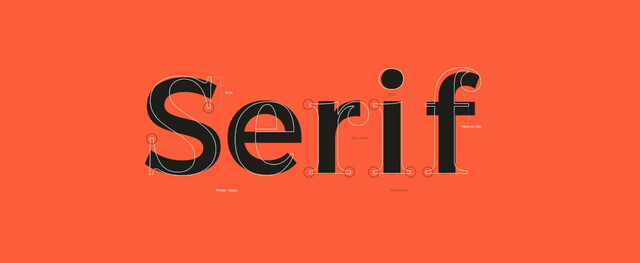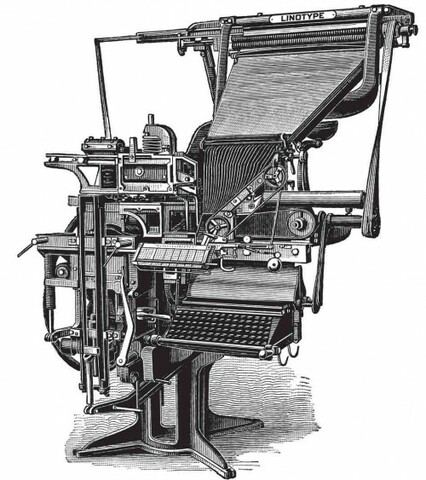
Alrededor de 1440, Johannes Gutenberg desarrolló en Alemania una técnica para elaborar moldes de tipo (ya conocida en China siglos atrás) que se utilizarían para la impresión de letras individuales, escogiendo el tipo textura como modelo, un tipo similar al trabajo de los escribas de la época. Fue con esta técnica que imprimió la Biblia de 42 líneas, la cual estuvo vigente por 500 años.
En 1486, Erhard Ratdolt publicó el primer catálogo de tipos que se haya producido (con fuentes romanas, griegas y capitales ornamentadas).
Con la llegada del siglo XVI, se inicia lo que se conoce como la época de oro de la tipografía francesa, destacando el trabajo de Henri y Robert Estienne, y especialmente Simon de Colines, que grabó varios tipos romanos, itálicos, versalitas, griegos y latinos. dos personajes importantes de la época como Geoffroy Tory y Claude Garamond, donde el segundo contribuyó con el tipo de letra que lleva su nombre, de gran legibilidad y elegancia.
Tal fue la importancia de la tipografía, que en 1692 el rey Luis XIV ordenó la creación de un comité de eruditos para la creación de un nuevo tipo que fuera diseñado bajo principios científicos. El resultado fue el tipo Jaugeon, de concepto racional, con letras de perfecto eje vertical y serifas simétricamente horizontales.
Pierre Simon Founier, inició la estandarización del tamaño de los tipos al publicar su Primera Tabla de Proporciones en 1737 y su primer libro de modelos, dos años después.
Y a partir de 1800 otra innovación tecnológica importante fue el tipo sans serif, que si bien había aparecido en un catálogo publicado por William Caslon IV en 1816, no causó impacto hasta tiempo después.
Linotype, inventada por Ottmar Mergenthaler, y especialmente la Monotype, de Tolbert Lanston, en 1880.
Apple Macintosh en 1982 fue el primer sistema operativo que mostraba diferentes tipos de letra para elegir y aplicar en las hojas de texto, lo cual fue una revolución.
Con la llegada de Internet, la tipografía y sus miles de creaciones pasaron a un nuevo escenario, la web, desde donde continúan su fecunda repercusión.